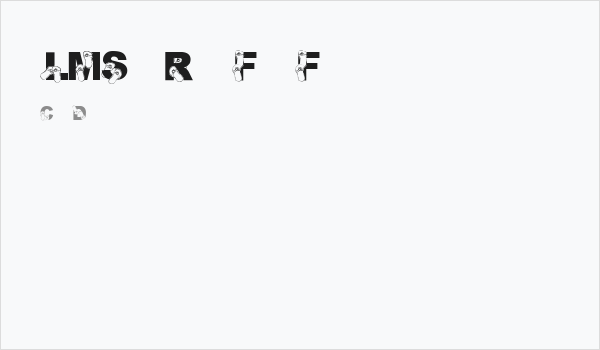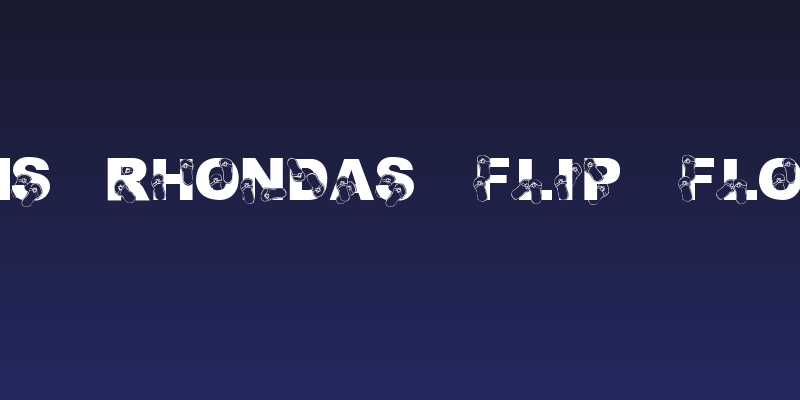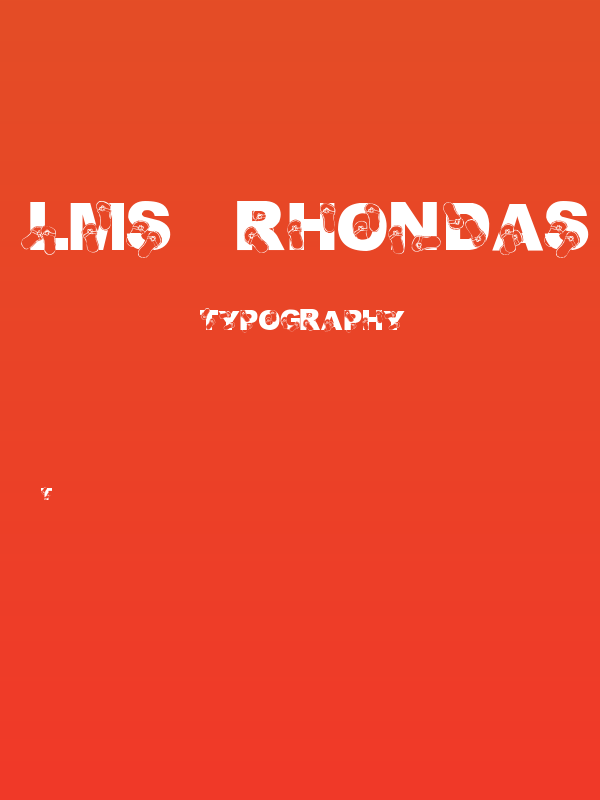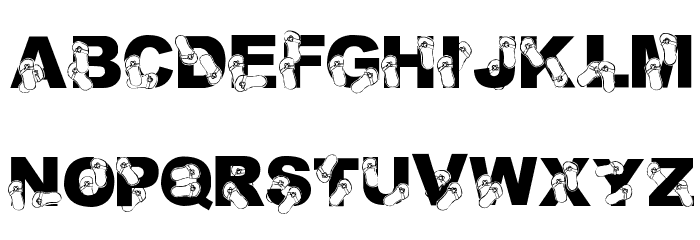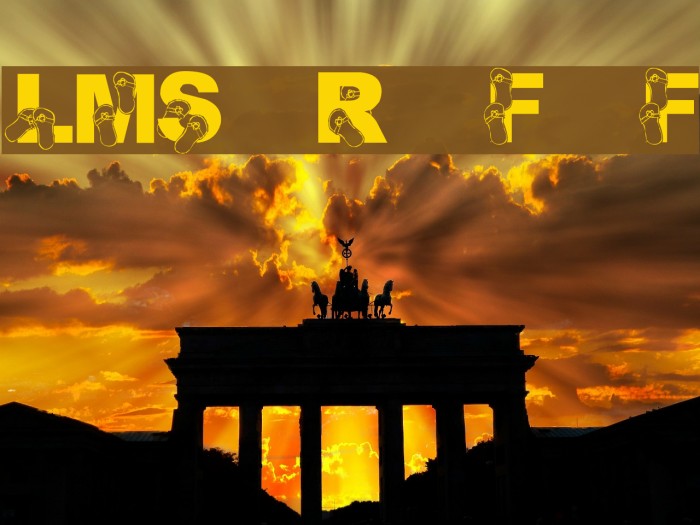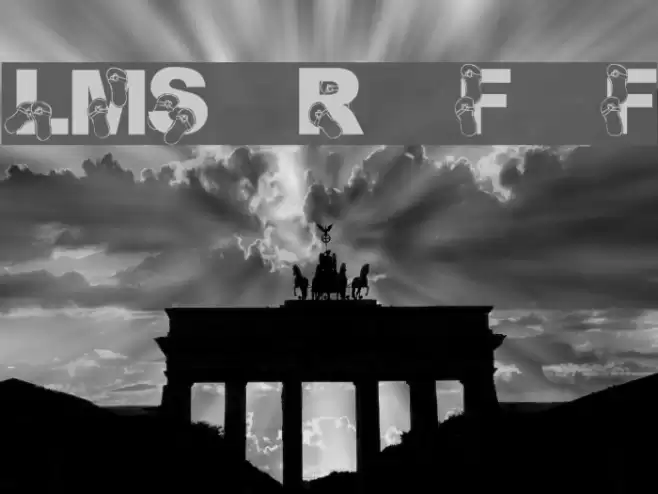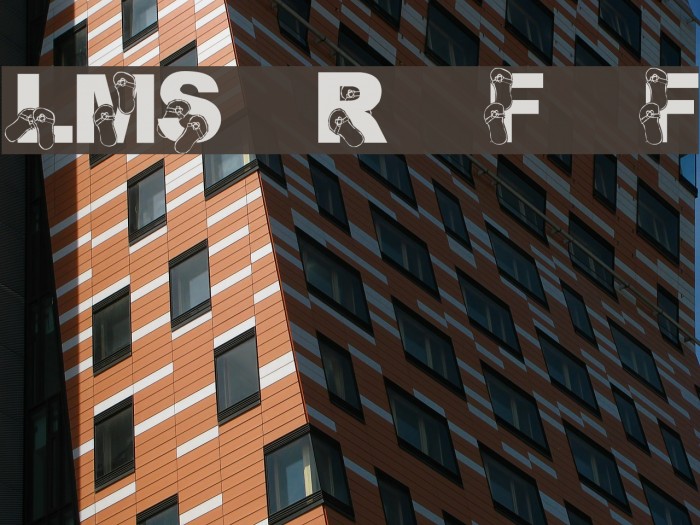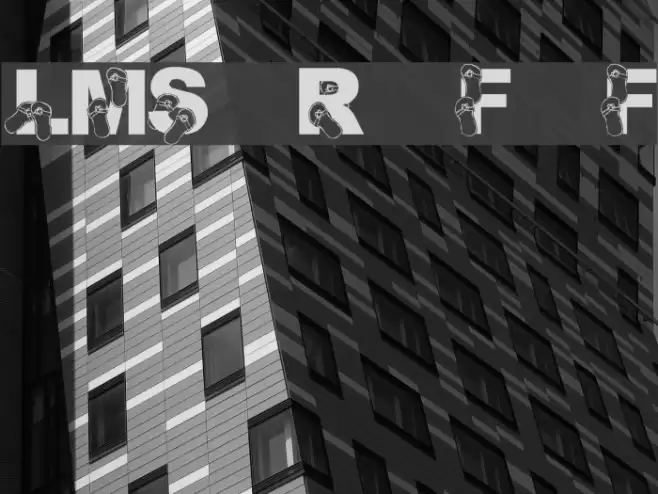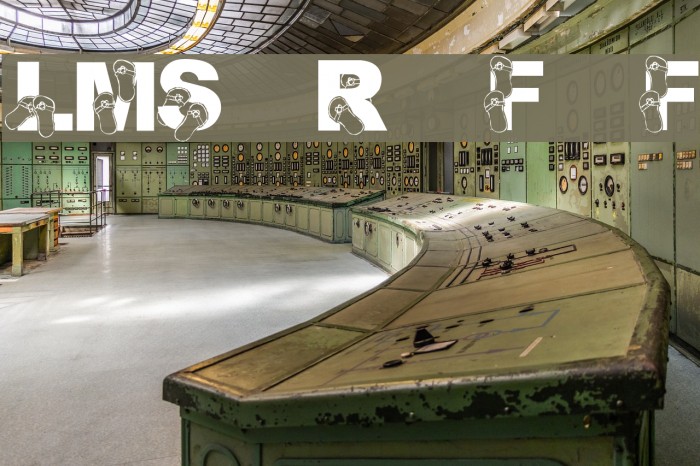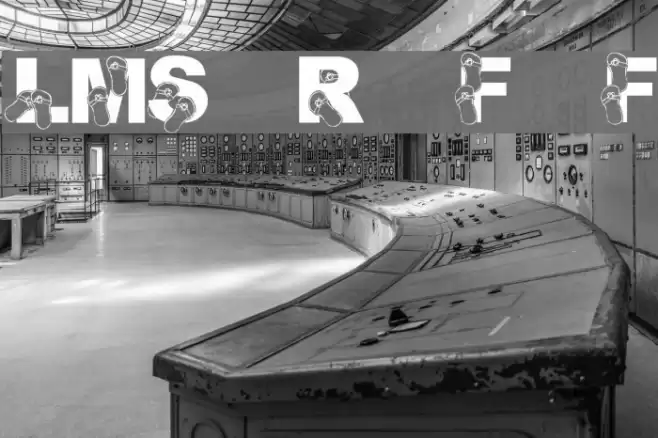
LMS Rhonda's Flip Flops Font
| Общий стиль | Playful, Whimsical |
| Область применения | Headlines, Logos, Invitations |
| Рекомендуемые проекты | Ideal for summer-themed designs, beach party invitations, playful branding, and children's book covers. |